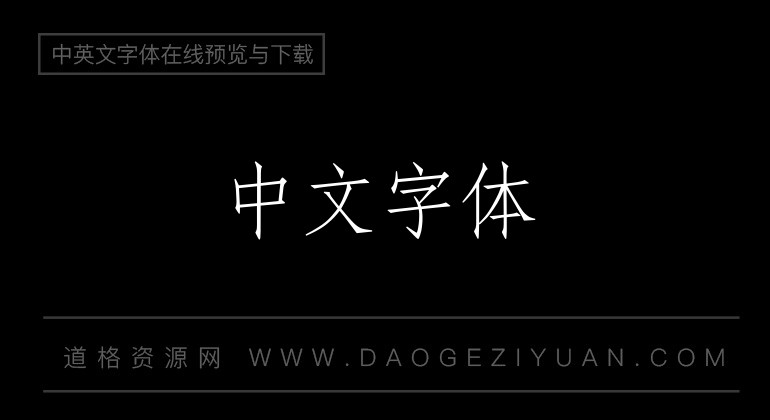
经典仿宋
经典仿宋字体是中国传统的文艺字体。它以清朝宋体为基础,在继承传统文艺字体的基础上,经过改进和发展,形成了一种新的文艺字体。经典仿宋字体的特点是圆润、稳重、端庄,其字形设计更加简洁、精细、大气,营造出一种大气、清新、秀丽的文艺氛围。它可以用于书法、文学、报纸、书籍等多种文字表现形式。
经典仿宋是一款非常不错的手写艺术字体,具有很好的视觉感,适合于文化类的宣传设计、商业类品牌的广告和产品包装设计以及个性化文字排版等较多场景。